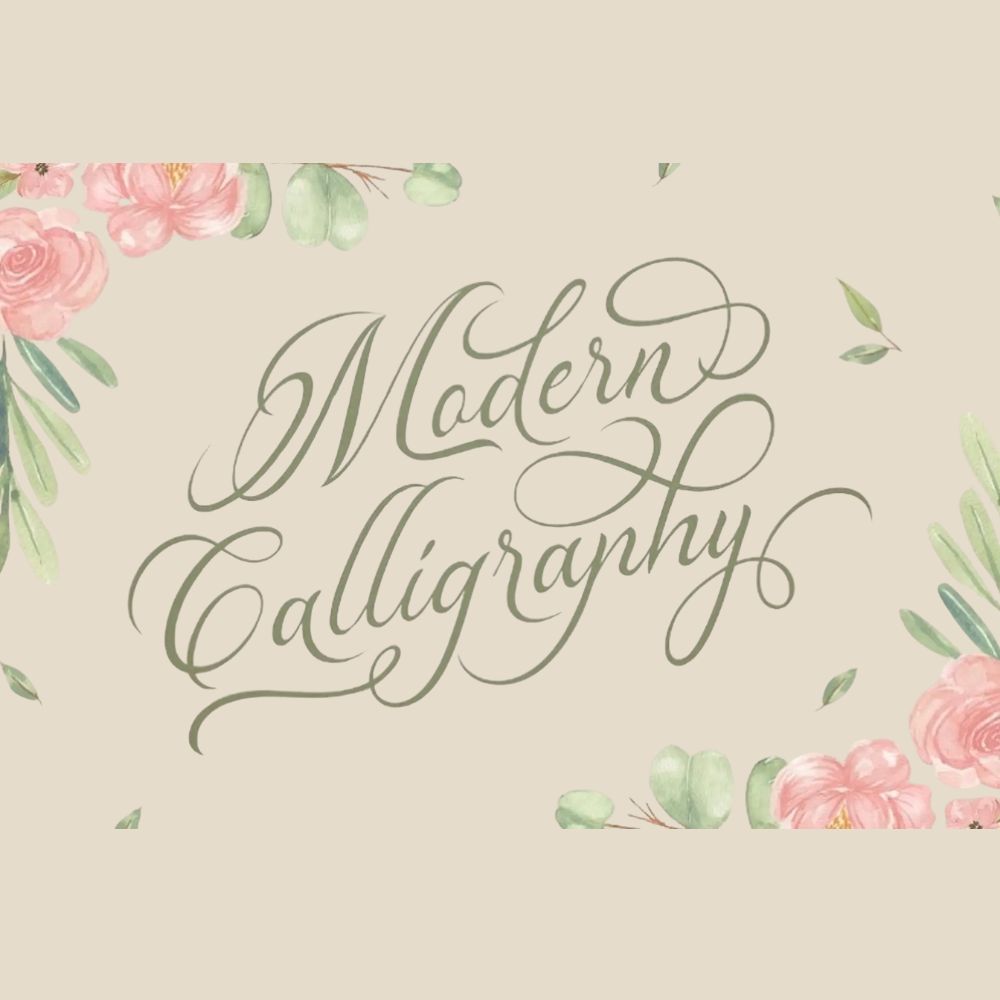
Calligraphy là nghệ thuật viết chữ đẹp với những đường nét bay bổng, mô phỏng sinh động kỹ thuật sử dụng bút mực truyền thống để tạo nên sự sang trọng và tinh tế. Các bộ font Calligraphy Việt hóa ra đời nhằm giúp người làm sáng tạo dễ dàng ứng dụng vẻ đẹp thủ công này vào các ấn phẩm đồ họa mà không gặp phải các lỗi hiển thị ký tự đặc biệt trong tiếng Việt.
Đặc điểm nghệ thuật từ các bộ font Calligraphy Việt hóa hiện nay
Điểm khác biệt rõ rệt của Calligraphy Việt hóa nằm ở cấu trúc nét chữ có độ thanh đậm biến thiên linh hoạt, tạo nên nhịp điệu mềm mại và cảm giác thủ công đầy cảm hứng. Khác với các kiểu chữ tiêu chuẩn cứng nhắc, font chữ Calligraphy Việt hóa mang lại chiều sâu cảm xúc, giúp bản thiết kế trở nên có hồn và thu hút người xem hơn. Việc sử dụng phiên bản đã được tối ưu hóa giúp các dấu thanh phối hợp cân đối với ký tự chính, giữ được vẻ đẹp nguyên bản của nghệ thuật thư pháp phương Tây.
Bên cạnh đó, các font chữ Calligraphy Việt hóa thường sở hữu hệ thống các ký tự thay thế phong phú. Bạn có thể dễ dàng tùy chỉnh những đường uốn lượn ở đầu hoặc cuối mỗi chữ cái để tạo ra sự khác biệt và dấu ấn cá nhân cho từng tác phẩm thiết kế. Đây là giải pháp hiệu quả cho những dự án yêu cầu sự thanh lịch, chuyên nghiệp và tính thẩm mỹ cao.
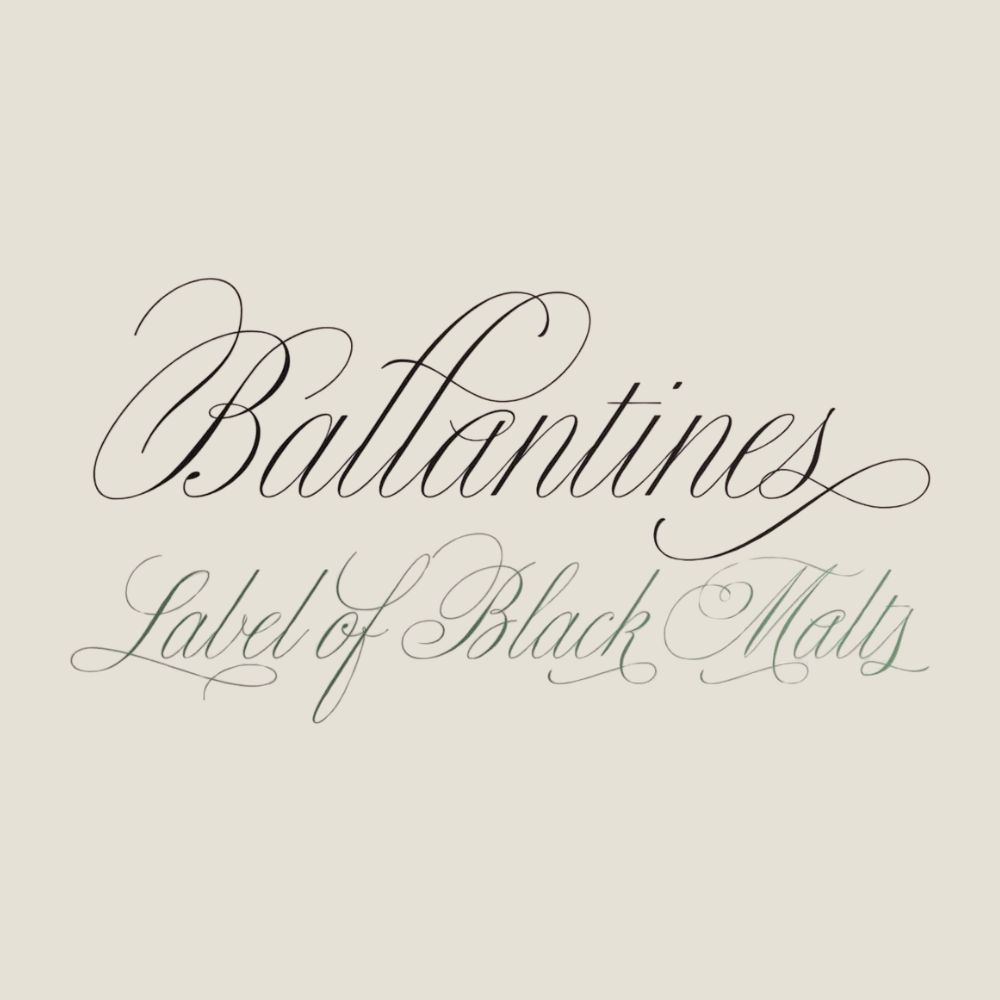
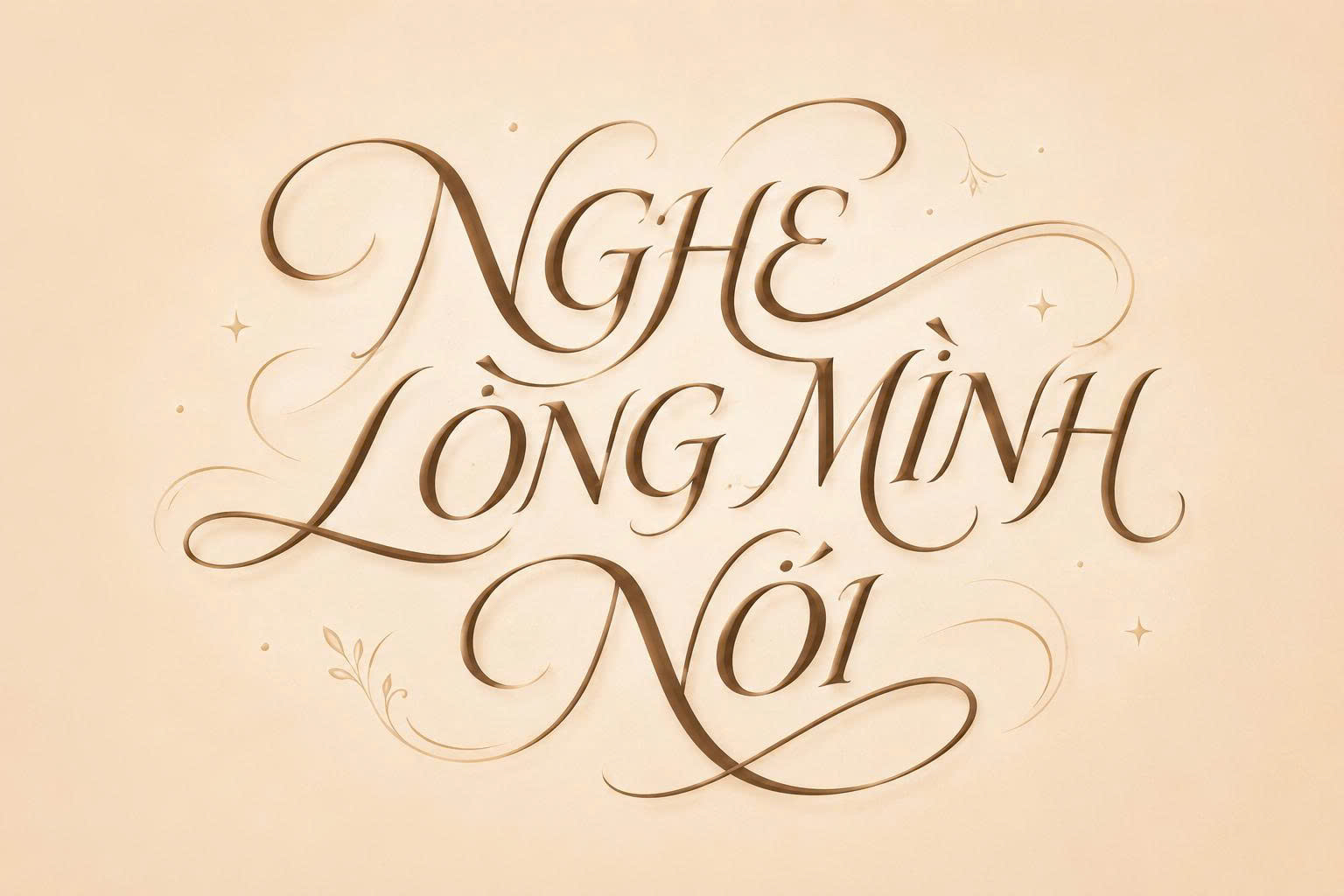
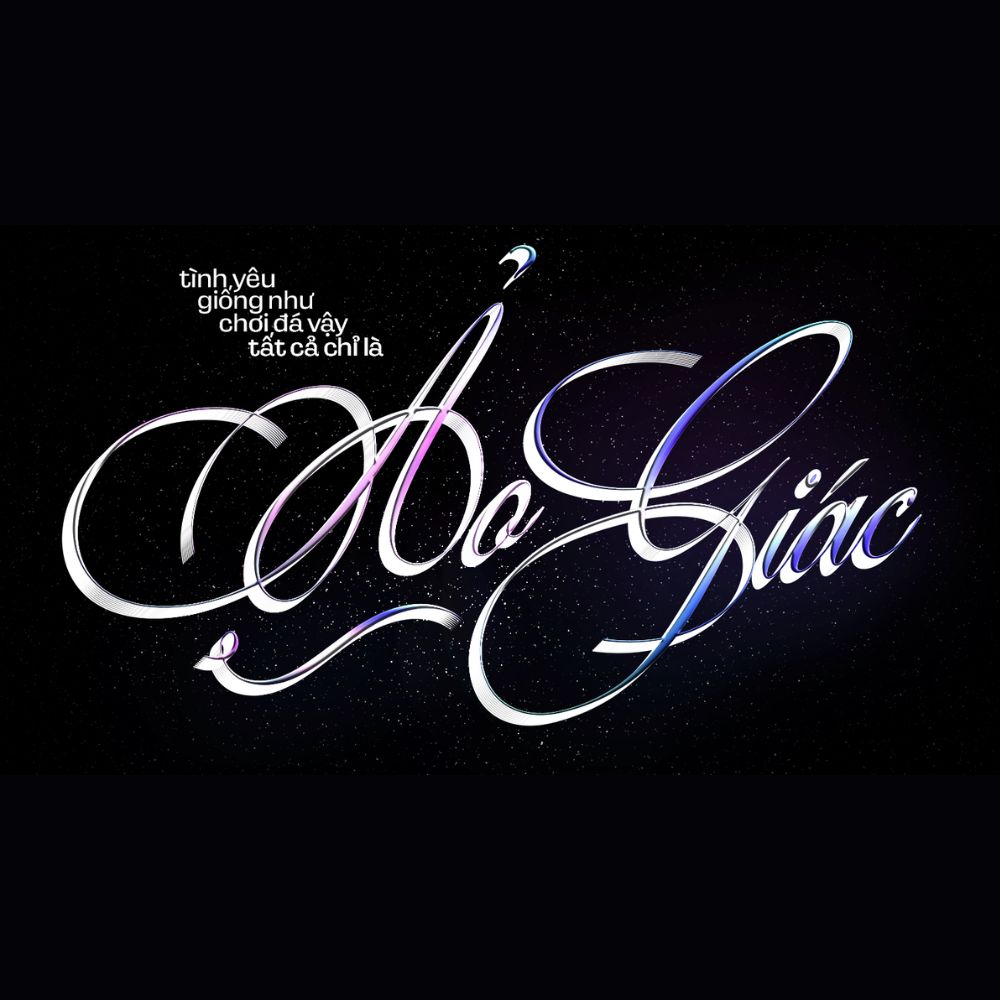
| Đặc tính nổi bật | Nét chữ liền mạch, độ uốn lượn cao |
| Mục đích sử dụng | Tiêu đề, thiệp mời, nhận diện thương hiệu |
Gợi ý phối hợp: Font Calligraphy thường có độ trang trí rất cao. Bạn nên kết hợp font chữ Calligraphy viết tay Việt hóa cùng các font không chân (Sans-serif) đơn giản cho phần văn bản chi tiết để tạo sự cân bằng bố cục và không làm rối mắt người đọc.
03 Ứng dụng phổ biến của Calligraphy font Việt hóa trong thiết kế
Nhờ vẻ ngoài thanh thoát và giàu tính nghệ thuật, bộ font này mang lại giá trị thẩm mỹ ổn định khi được đưa vào thực tế trang trí và quảng bá:
- Nhận diện cho Homestay và Nhà hàng cao cấp: Những nét chữ mềm mại của Calligraphy Việt hóa rất phù hợp để làm bảng tên phòng, bảng menu hoặc biển hiệu cho các khu nghỉ dưỡng, homestay container mang phong cách trang nhã và gần gũi với thiên nhiên.
- Thiết kế bao bì và quà tặng doanh nghiệp: Sử dụng font Calligraphy giúp các sản phẩm quà tặng hoặc bao bì cao cấp tăng thêm giá trị tinh thần, thể hiện sự chỉn chu và tôn trọng đối với người nhận.
- Trang trí nội thất và bảng chữ nghệ thuật: Bạn có thể dùng font này để in decal dán tường hoặc làm tranh quotes trang trí cho văn phòng, phòng khách nhà lắp ghép nhằm tạo điểm nhấn đầy tinh tế cho không gian sống.
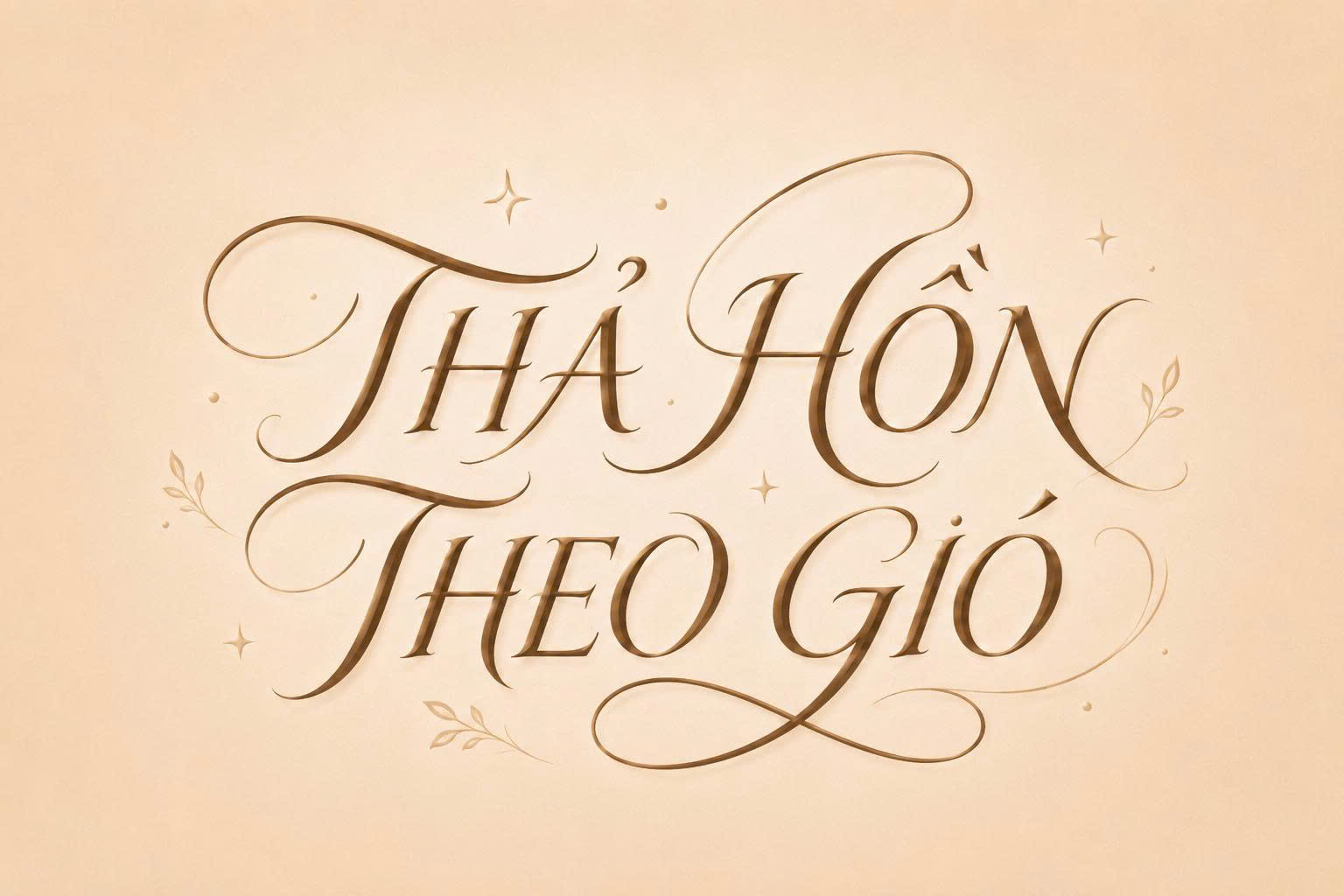
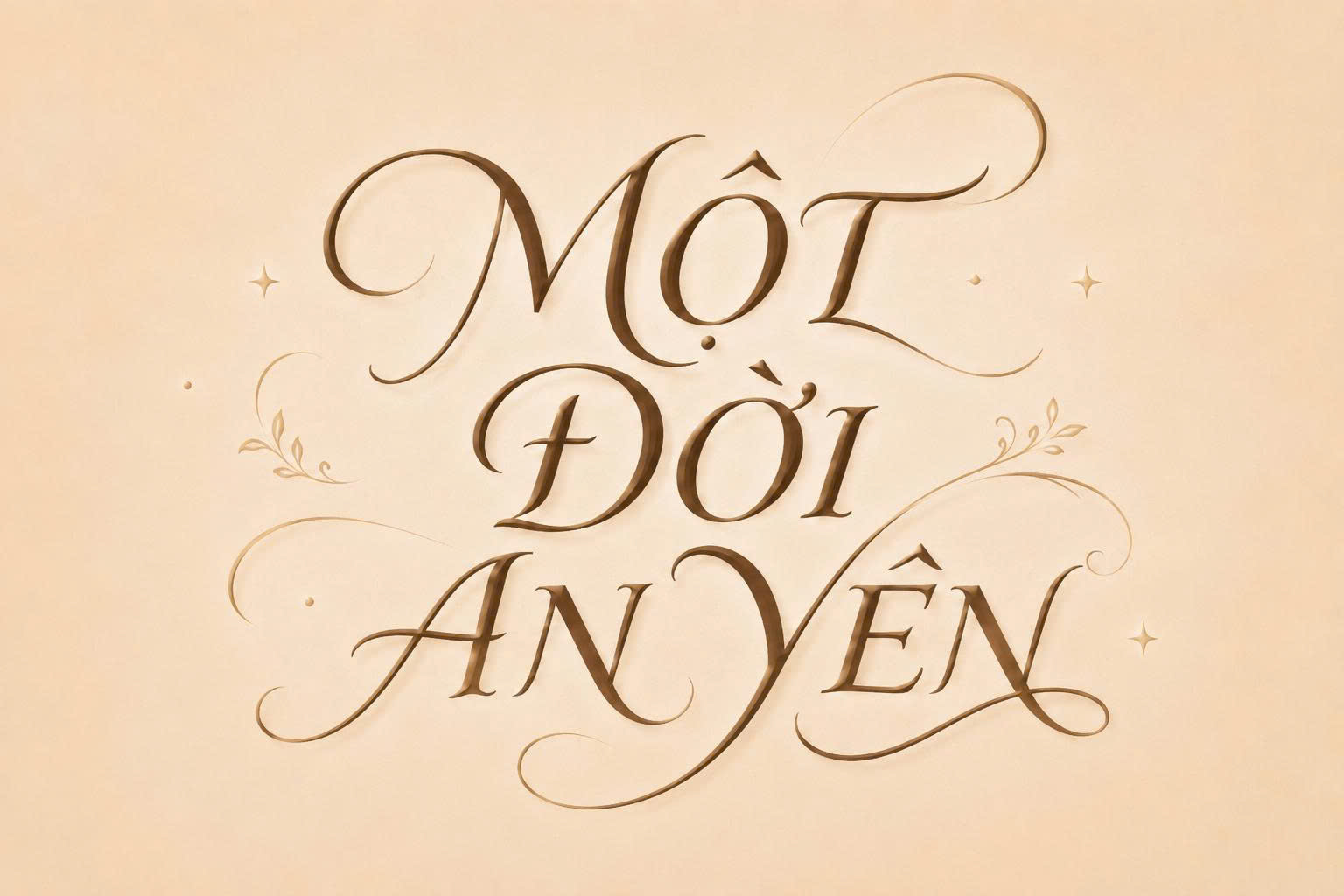
03 Lưu ý kỹ thuật khi sử dụng font chữ Calligraphy Việt hóa trong bố cục
Để khai thác hiệu quả vẻ đẹp của font chữ Calligraphy Việt hóa mà không làm giảm tính chuyên nghiệp của sản phẩm, người thiết kế nên lưu tâm một số điểm sau:
- Hạn chế sử dụng toàn bộ chữ in hoa: Đặc trưng của font Calligraphy là các nét nối chữ thường, việc viết hoa toàn bộ từ sẽ làm mất đi tính nhịp điệu và gây khó khăn cho việc nhận diện mặt chữ.
- Kiểm soát khoảng cách giữa các chữ: Do nét chữ có độ vươn rộng, bạn cần nới rộng khoảng cách dòng (leading) để các nét uốn lượn không bị chồng chéo, giúp văn bản thông thoáng và dễ đọc hơn.
- Tránh dùng cho đoạn văn bản dài: Chỉ nên sử dụng font việt hoá Calligraphy cho tiêu đề, tên thương hiệu hoặc các trích dẫn ngắn. Sử dụng cho các đoạn nội dung dài sẽ gây mỏi mắt và làm mất đi trọng tâm của bản thiết kế.